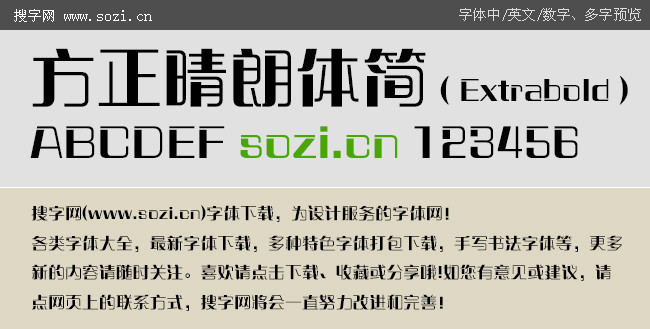
方正晴朗體簡Extrabold
搜字網(wǎng)提供一款方正晴朗體簡中文字體下載,晴朗體字體爽朗,充滿陽光氣息,所以命名為“晴朗體”。 晴朗體普遍每一個字只有兩直劃是粗的,其余橫直都是細(xì)的,左邊上下直角,右邊上下是圓角,形成一個強烈對比,所以粗細(xì)的視覺很平均,不會有太重和太輕的感受,排版畫刊更有舒服感覺,工整中還少許動感,美觀齊整,空間分布平均,適合金融、保險行業(yè),汽車行業(yè),投資行業(yè),電子產(chǎn)品的商業(yè)宣傳和包裝設(shè)計!